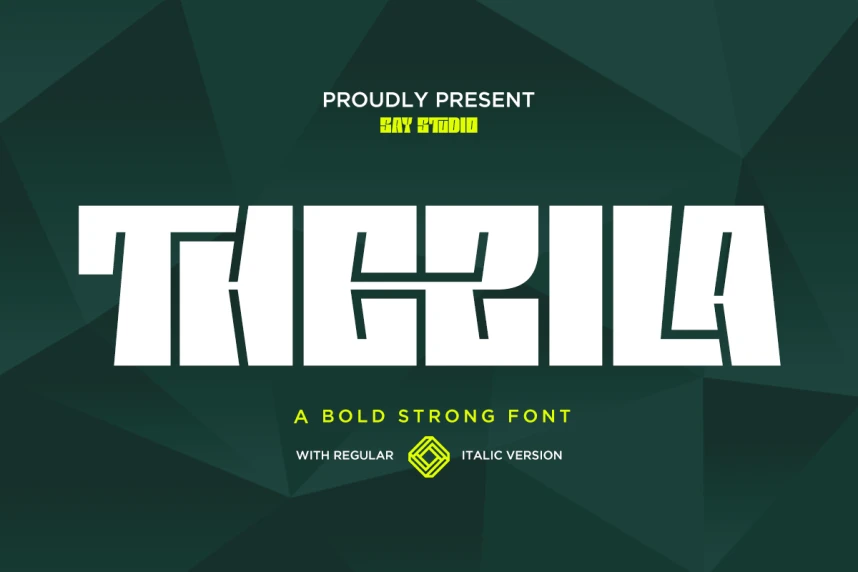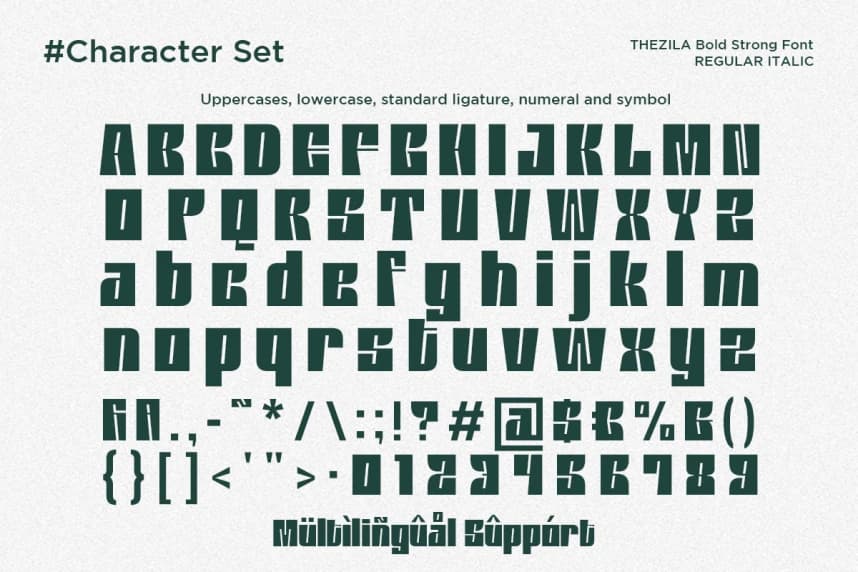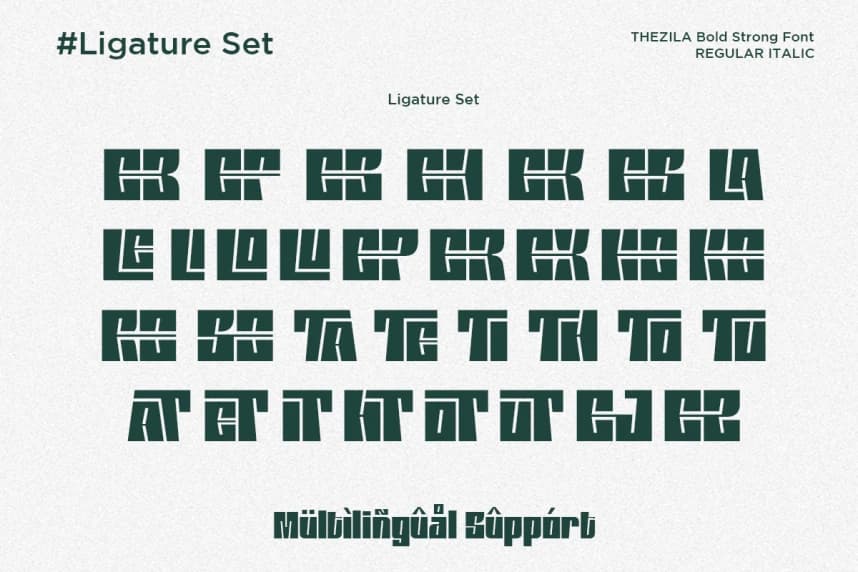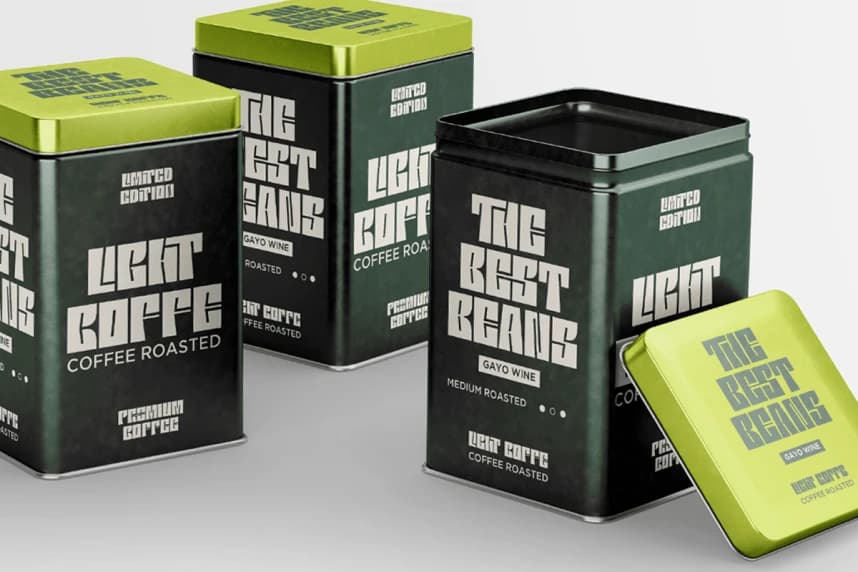
Thezila Font
Thezila Font, modern ve fütüristik bir dokunuşa sahip olarak maksimum etki yaratmak üzere tasarlanmış cesur ve güçlü bir gösterim yazı tipidir. Keskin açılar ve güçlü geometrik yapılarla inşa edilmiş olan bu yazı tipi, çarpıcı bir görsel varlık yaratır ve hemen dikkat çeker.